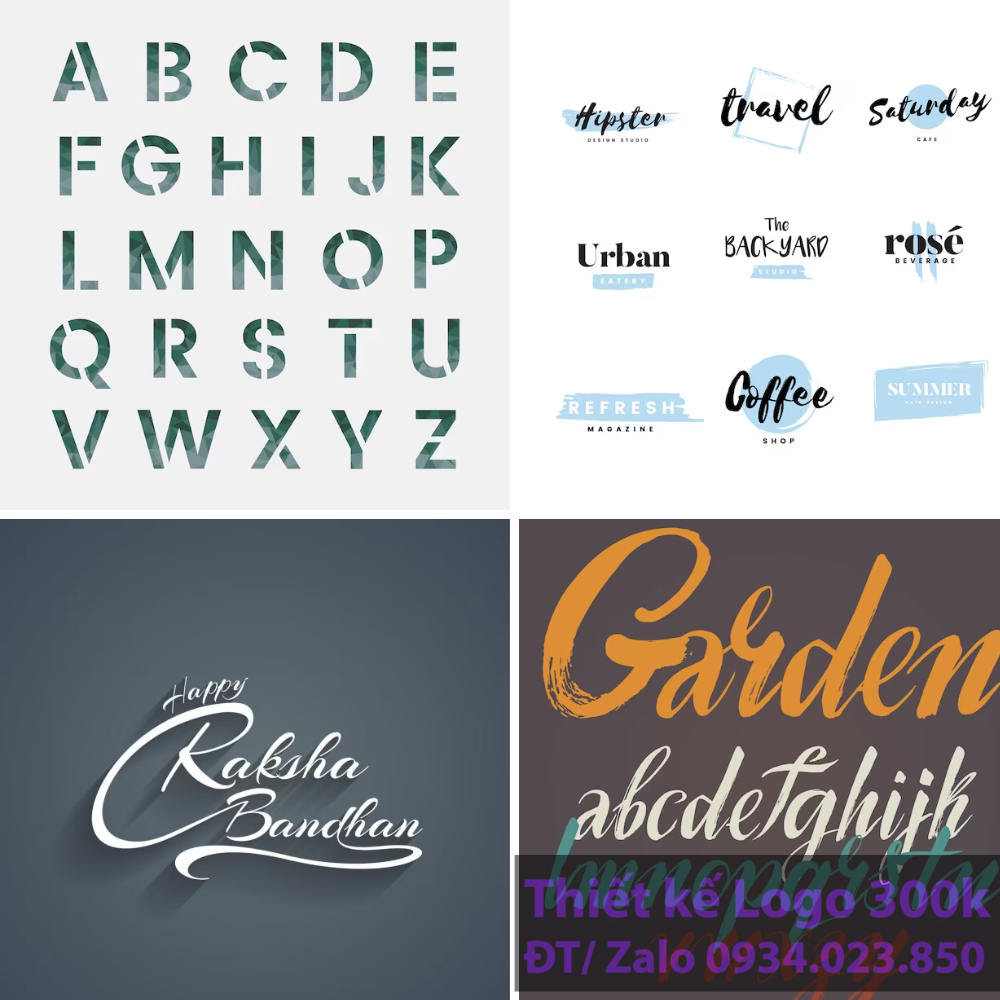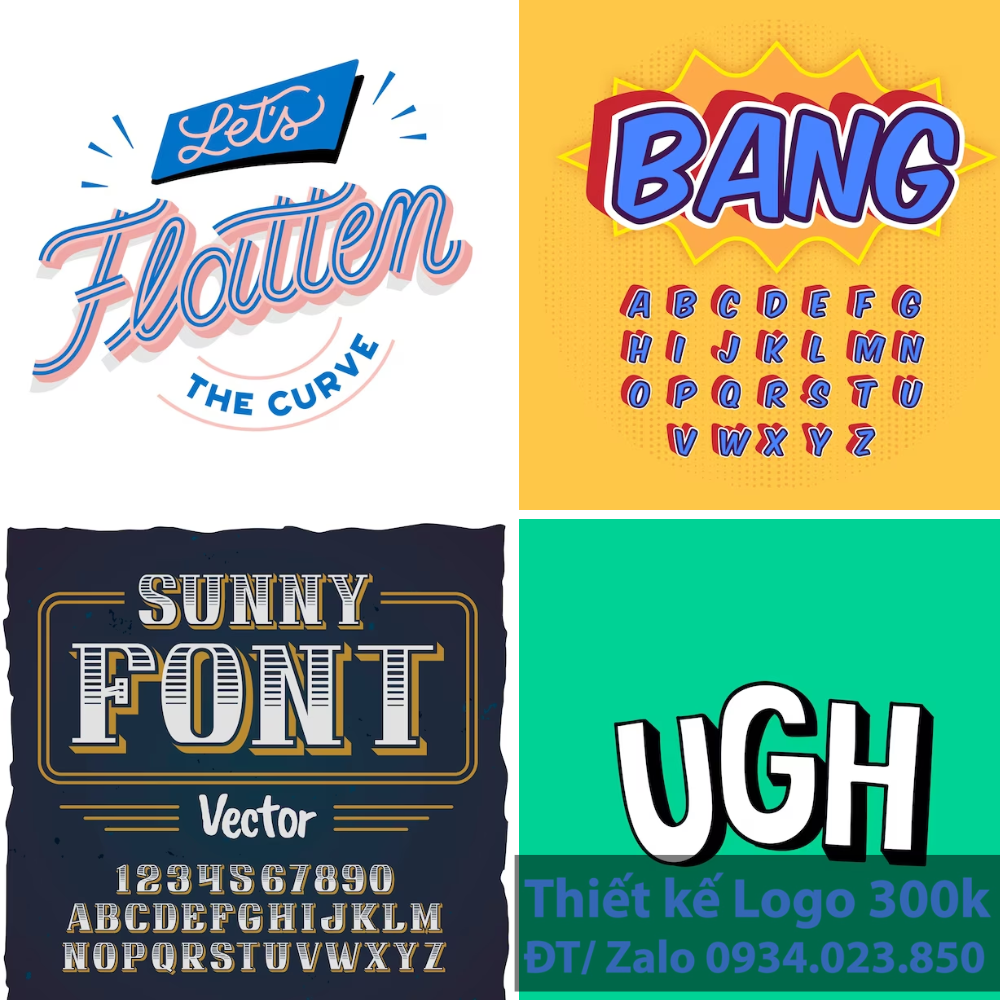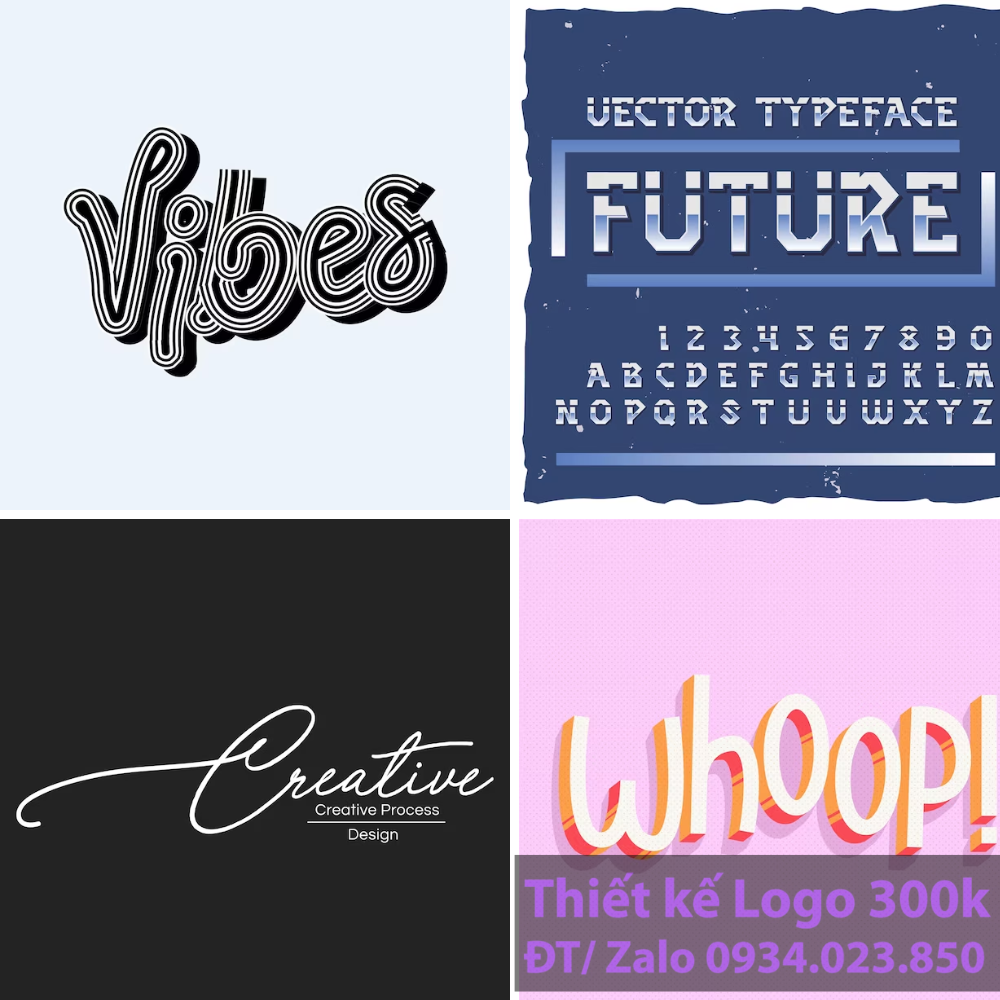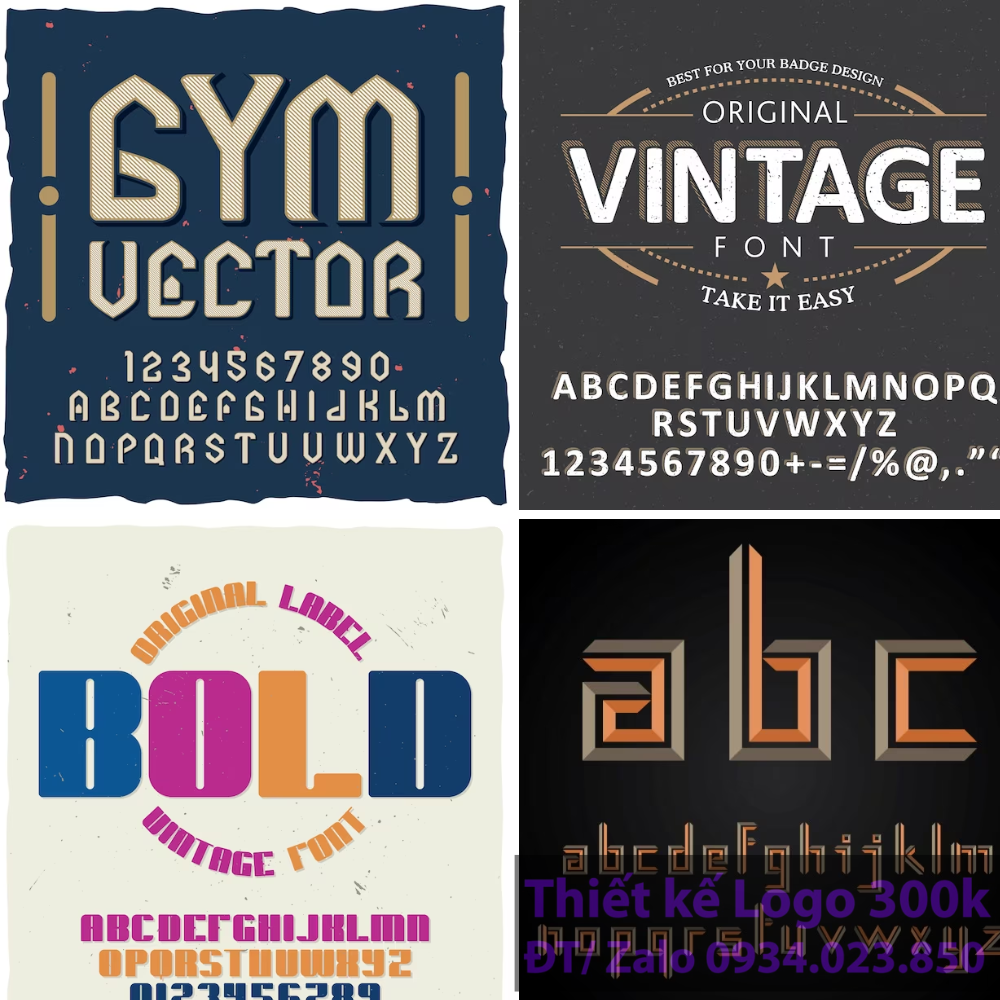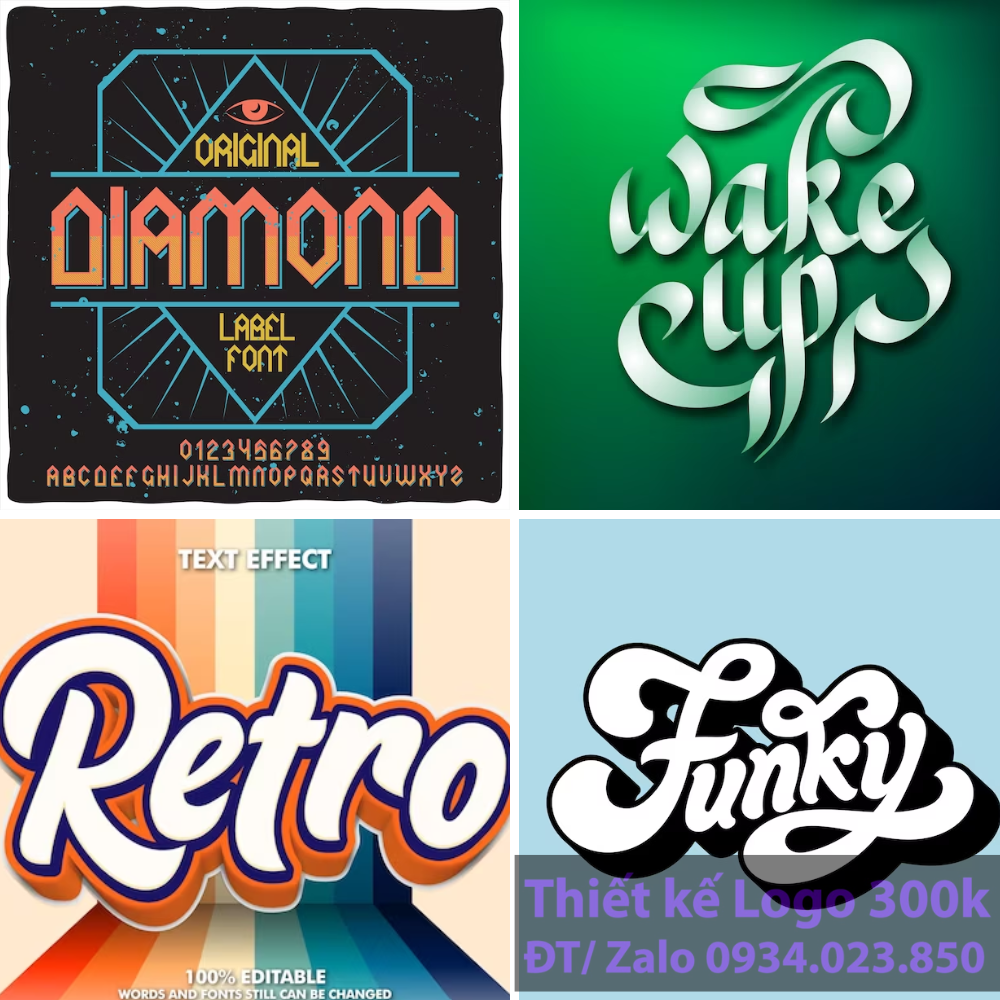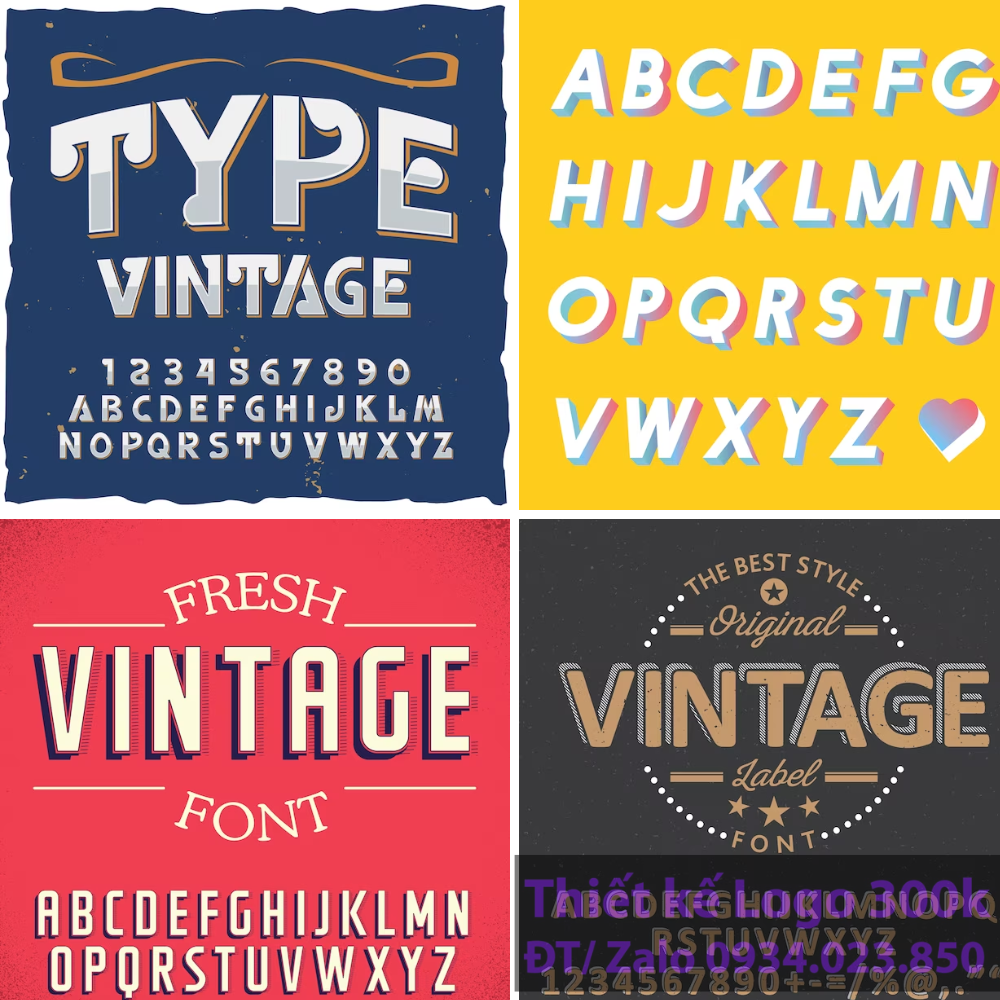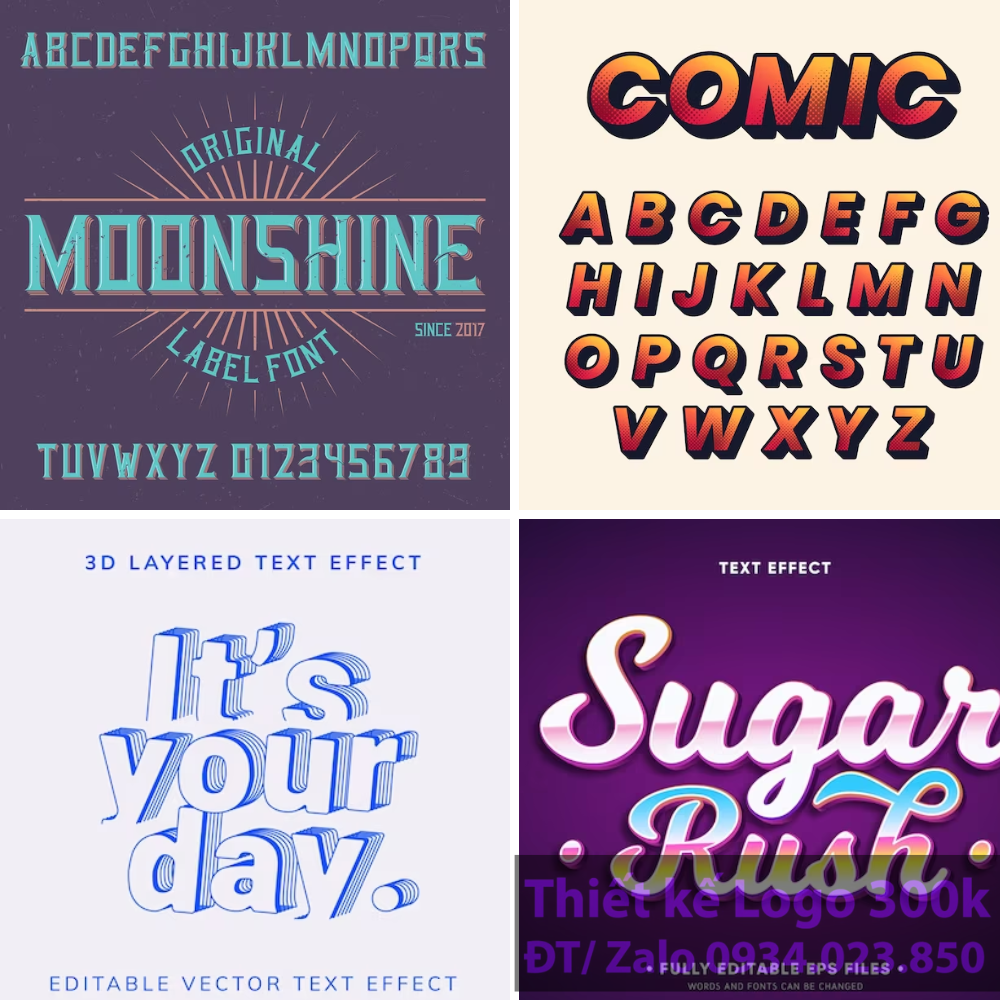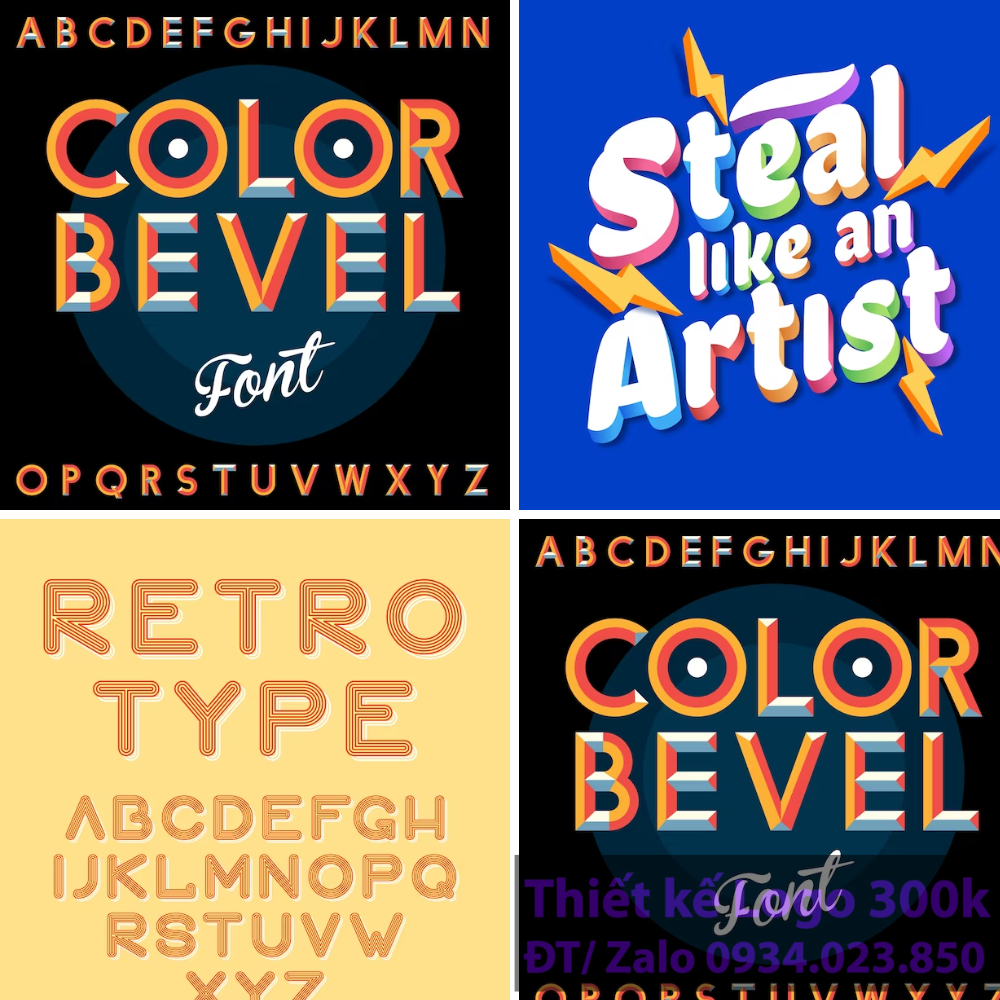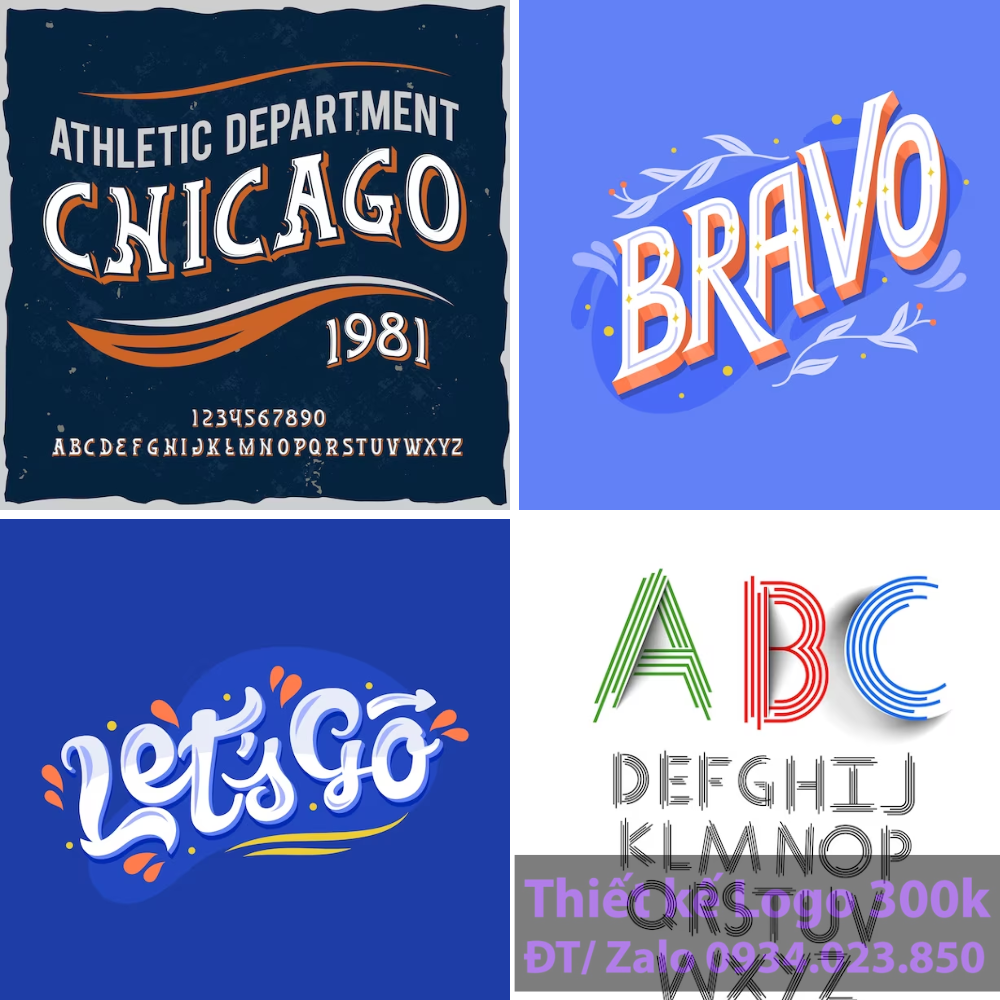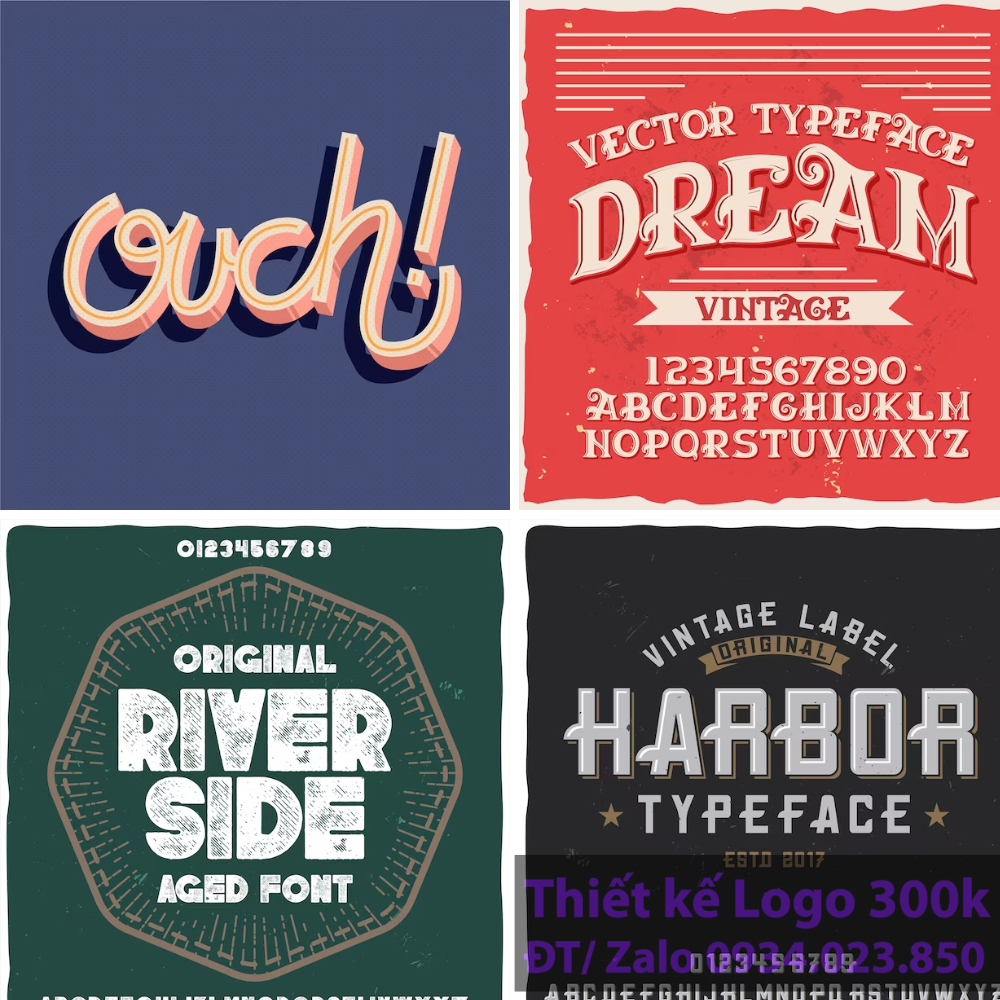
Trong thế giới font chữ trong thiết kế logo, font chữ không chỉ đơn giản là phương tiện để truyền đạt thông tin mà còn là yếu tố quan trọng tạo nên bản sắc và sức hút cho thương hiệu. Mỗi font chữ trong thiết kế logo mang một phong cách, một tính cách riêng, từ đó góp phần vào việc xây dựng hình ảnh và thông điệp của thương hiệu. Nhìn chung, font chữ trong thiết kế logo không chỉ là phần tử thiết kế mà còn là ngôn ngữ nghệ thuật, là cầu nối giữa thương hiệu và người tiêu dùng. Sự lựa chọn và sử dụng font chữ một cách khéo léo và sáng tạo có thể nâng cao giá trị thương hiệu và tạo ra sự khác biệt trên thị trường.
Lịch sử của font chữ trong thiết kế logo
Thập niên đầu
Lịch sử của font chữ trong thiết kế logo bắt đầu từ những năm đầu của ngành in ấn và quảng cáo. Trong giai đoạn này, font chữ chủ yếu được sử dụng để tạo điểm nhấn và thu hút sự chú ý của người xem. font chữ trong thiết kế logo cổ điển như Garamond hay Bodoni thường được ưa chuộng trong giai đoạn này vì sự rõ ràng và đẳng cấp của chúng.
Sự Đổi Mới và Phát Triển
Vào thế kỷ 20, với sự bùng nổ của công nghiệp quảng cáo và thiết kế đồ họa, font chữ trở nên đa dạng và phong phú hơn bao giờ hết. Các nhà thiết kế bắt đầu thử nghiệm với các kiểu chữ độc đáo và sáng tạo, từ đó mở ra một kỷ nguyên mới cho thiết kế logo. Những font chữ trong thiết kế logo như Helvetica hay Futura được tạo ra, không chỉ mang tính ứng dụng cao mà còn thể hiện tính cách mạnh mẽ, hiện đại.
Kỷ Nguyên Kỹ Thuật Số
Với sự ra đời của máy tính và công nghệ kỹ thuật số, việc tạo và sử dụng font chữ trong thiết kế logo trở nên dễ dàng và phổ biến hơn. Các nhà thiết kế không chỉ có quyền truy cập vào một thư viện font chữ trong thiết kế logo khổng lồ mà còn có thể tạo ra font chữ của riêng mình. Sự phát triển này mở ra không gian sáng tạo không giới hạn cho thiết kế logo.
Vai Trò của font chữ trong thiết kế logo
Truyền Đạt Thông Điệp Thương Hiệu
Font chữ trong logo không chỉ để hiển thị tên thương hiệu mà còn góp phần truyền đạt thông điệp và giá trị cốt lõi của thương hiệu đó. Mỗi font chữ mang một ý nghĩa riêng: một font Serif truyền thống mang đến cảm giác uy tín và lịch sử; font Sans-serif hiện đại thể hiện sự tinh gọn và tiên tiến; trong khi đó, font Script lại mang đến vẻ đẹp mềm mại và nghệ thuật.
Tạo Ấn Tượng và Phân Biệt
Font chữ là một trong những yếu tố đầu tiên mà người xem nhận biết khi nhìn vào một logo. Sự lựa chọn font chữ phù hợp có thể tạo ra ấn tượng mạnh mẽ và giúp thương hiệu nổi bật giữa đám đông. Một font chữ độc đáo và đặc trưng có thể trở thành biểu tượng nhận dạng thương hiệu, giúp người tiêu dùng dễ dàng nhận biết và nhớ đến thương hiệu.
Tối Ưu Hóa Sự Nhận Biết
Trong môi trường cạnh tranh khốc liệt của thị trường hiện nay, một logo với font chữ dễ đọc và dễ nhận biết có thể là chìa khóa thành công. Font chữ giúp tối ưu hóa sự nhận biết của logo trên các phương tiện truyền thông khác nhau, từ in ấn đến kỹ thuật số.
Tầm Quan Trọng của font chữ trong thiết kế logo trong Xây Dựng Thương Hiệu
Font chữ trong thiết kế logo không chỉ là phần tử thẩm mỹ mà còn là yếu tố then chốt trong việc xây dựng và củng cố thương hiệu. Trong bối cảnh thương hiệu ngày càng cạnh tranh, font chữ không chỉ giúp truyền đạt thông tin mà còn là phương tiện quan trọng để tạo ra sự nhận diện và liên kết cảm xúc với người tiêu dùng.
1. Tạo Dấu Ấn Độc Đáo
Font chữ giúp thương hiệu tạo ra một dấu ấn độc đáo. Khi một font chữ được thiết kế hoặc lựa chọn một cách cẩn thận, nó có thể phản ánh tính cách và giá trị cốt lõi của thương hiệu. Ví dụ, một font chữ mạnh mẽ và đơn giản như Helvetica có thể truyền đạt sự hiện đại và chuyên nghiệp, trong khi một font chữ trong thiết kế logo cầu kỳ như Papyrus có thể thể hiện sự sáng tạo và nghệ thuật.
1. Kết Nối Cảm Xúc với Khách Hàng
Font chữ có khả năng kết nối cảm xúc với khách hàng. Mỗi font chữ gợi lên những cảm xúc và hình ảnh khác nhau, từ đó giúp khách hàng liên tưởng và gắn bó với thương hiệu. Một font chữ ấm áp và thân thiện có thể tạo cảm giác gần gũi, trong khi một font chữ trong thiết kế logo lịch lãm và sang trọng có thể gợi lên sự tinh tế.